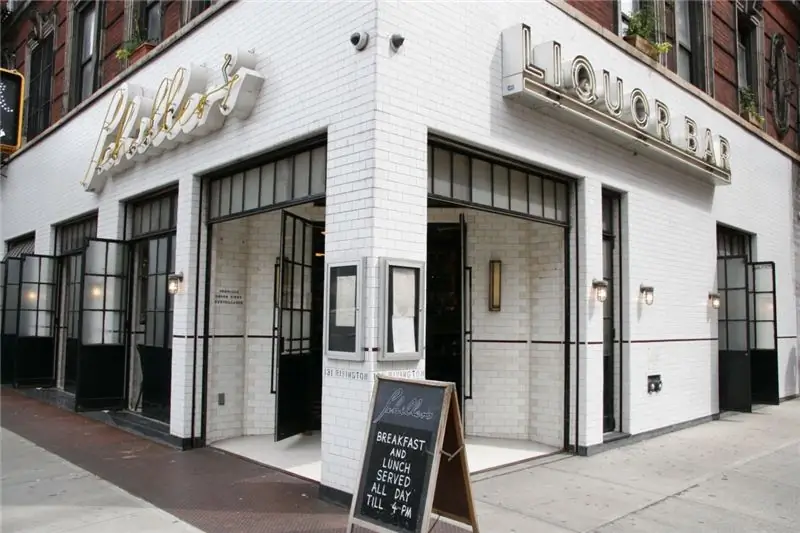
Шиллера
С двумя вечно сексуальными шрифтами, украшающими вход Шиллера, у вас будет возможность сделать фотосессию еще до того, как вы войдете внутрь. (Там тоже много других, не волнуйтесь).
Чайный салон Ном Ва
Вывеска Nom Wah Tea Parlor, прекрасно выветренная, выглядит заслуживающей доверия. Его винтажный вид говорит о том, что он уже знает, что вы отлично проведете здесь время.
Магазин яиц
Мы чувствуем себя друзьями с этим знаком. Если возможно, что шрифт может поднять настроение, мы нашли победителя в Egg Shop.
Грязный французский
Да неон, да. В то время как идеально продуманный свет служит для того, чтобы просто обозначить пространство, он также может добавить ощущение тайны или даже озорства, как это, безусловно, делает эта ярко-розовая красавица.
Американский Два выстрела
Этот шрифт настолько хорош, что мы бы хотели, чтобы он был установлен по умолчанию в Google Chrome.
Красота и Эссекс
Каждая отдельная лампочка словно притягивает нас ближе. Что такого в этом способе освещения, что так пленяет зрителя? Это небольшое ностальгическое событие принесло этому знаку место в нашем списке.
Холодное пиво Грейди
Ура цвету! Вывеска делает такое же смелое заявление на улице, как и на полке, выделяясь среди тихих вывесок и незапоминающихся этикеток.
Счастливые кости
Этот знак, кажется, делает невозможное, идеально сочетая минимализм с индустриальным оттенком.
Пицца любит Эмили
Еще один идеальный неоновый момент, вывеска Эмили настолько яркая, что ей не нужно быть огромной, чтобы выделяться. (Кроме того, если вы планируете в ближайшее время быть в Бруклине, это место обязательно нужно посетить!).
Субботний прибой в Нью-Йорке
Иногда знак просто самый крутой. Если это не вдохновит вас на следующую покупку нестандартных канцелярских товаров, мы не знаем, что будет.
Рефайнери Отель
Иногда нужно смотреть вверх. Этот знак очень удачно играет с размером, вызывая ощущение современности, не выглядя при этом ничуть натянутым или банальным.
Спанджер Знаки
Как мы можем иметь вывеску без реальной компании-вывески? Бонусные баллы за использование не одного, а двух смехотворно крутых шрифтов. Кто-нибудь еще ощущает здесь атмосферу Уэса Андерсона?
Расс и дочери
Помимо того, что вывеска Russ & Daughters выглядит и ощущается очень старым Нью-Йорком, она выглядит так же хорошо днем, как и ночью - нелегкий подвиг для неона.
Магазин гигантских сэндвичей Tiny's
Чистый, приятный для глаз минималистичный шрифт Tiny заставляет вас хотеть пойти домой и привести все в порядок.
Роберта
Шрифт Роберты и даже невзрачный размер вывески ресторана создают ощущение, что вам здесь рады, как будто вы идете домой.